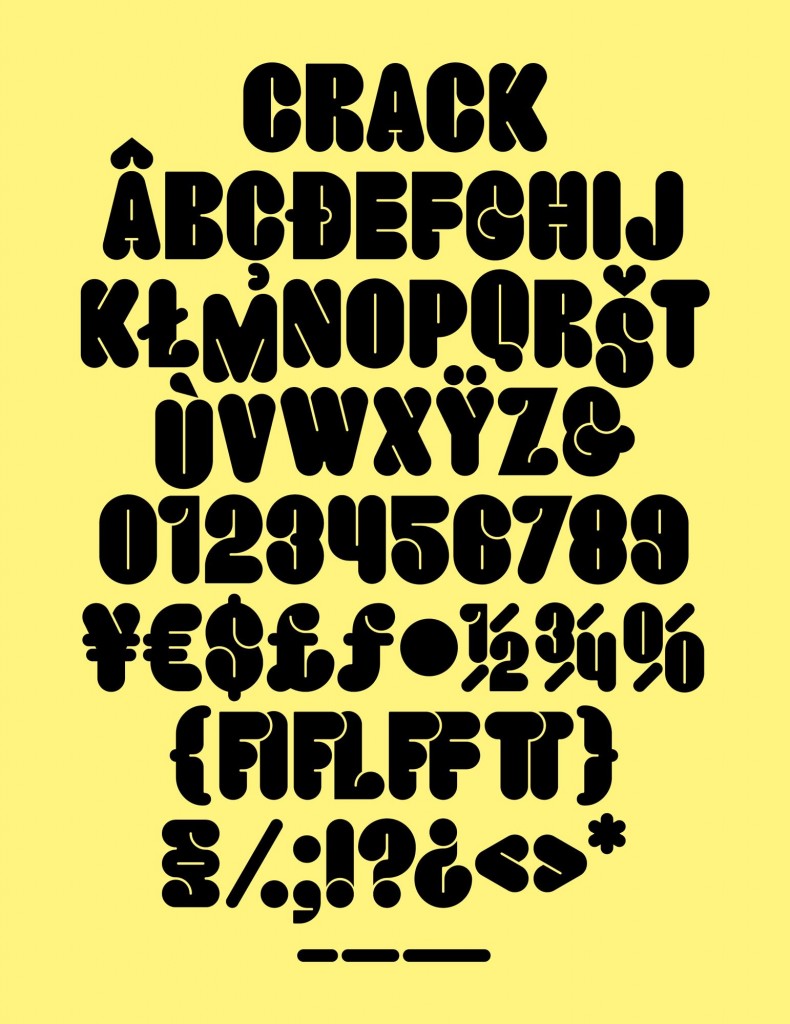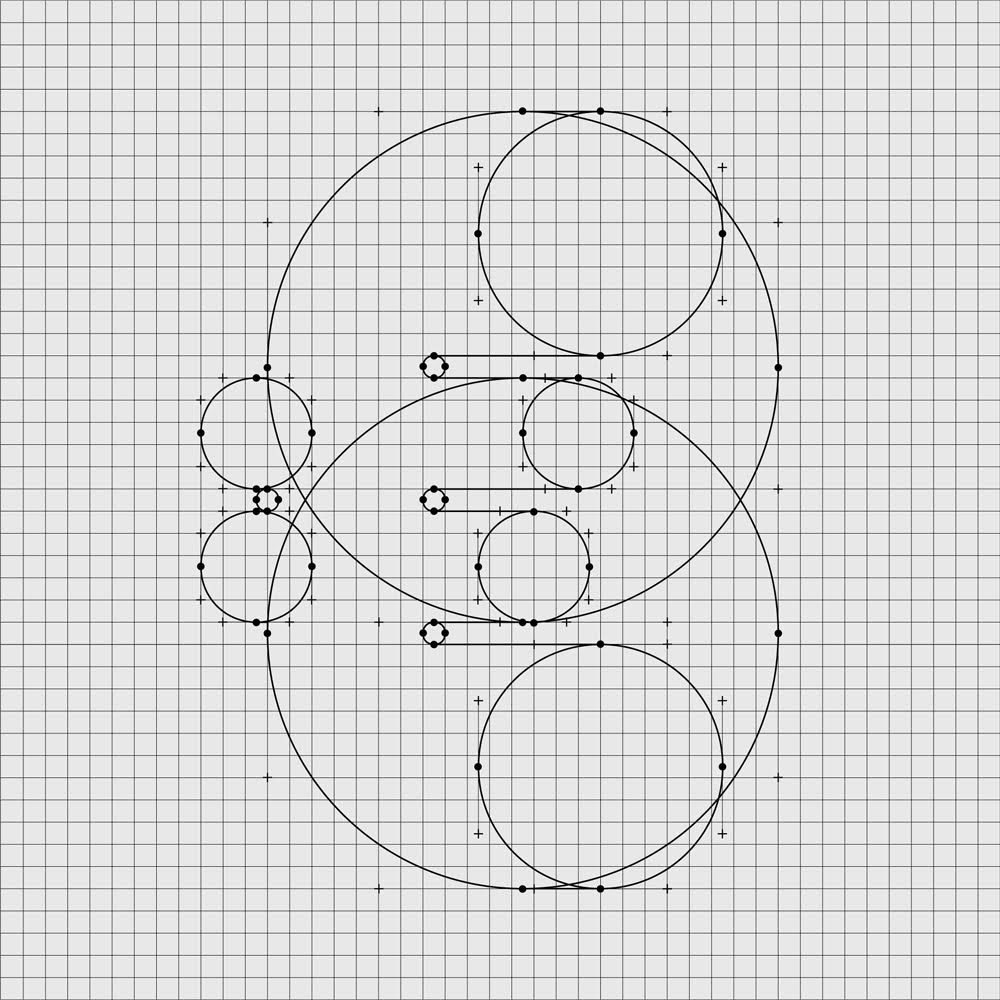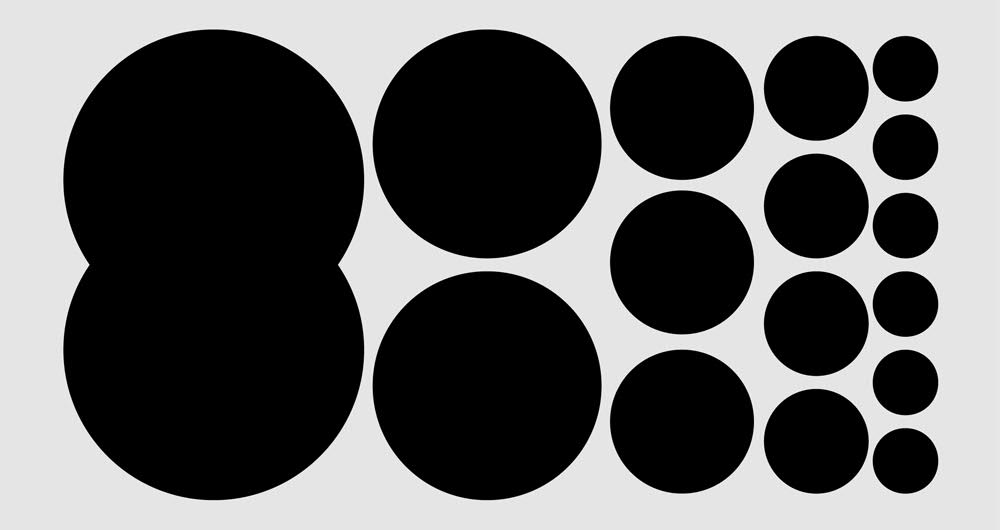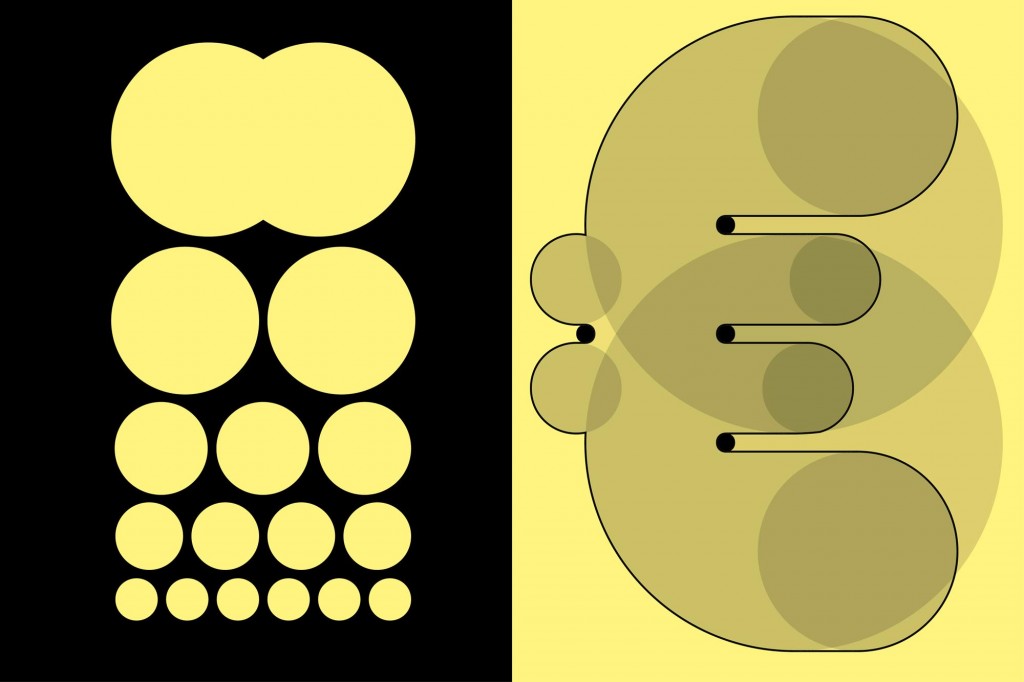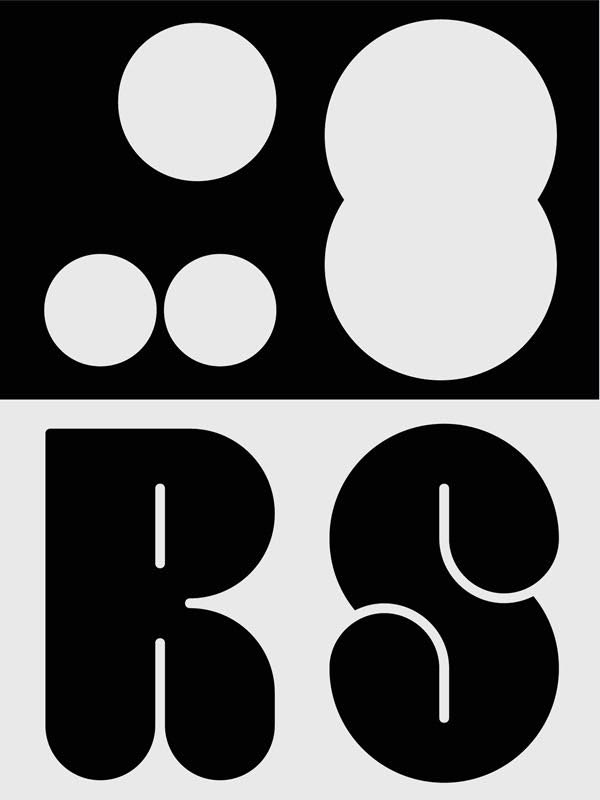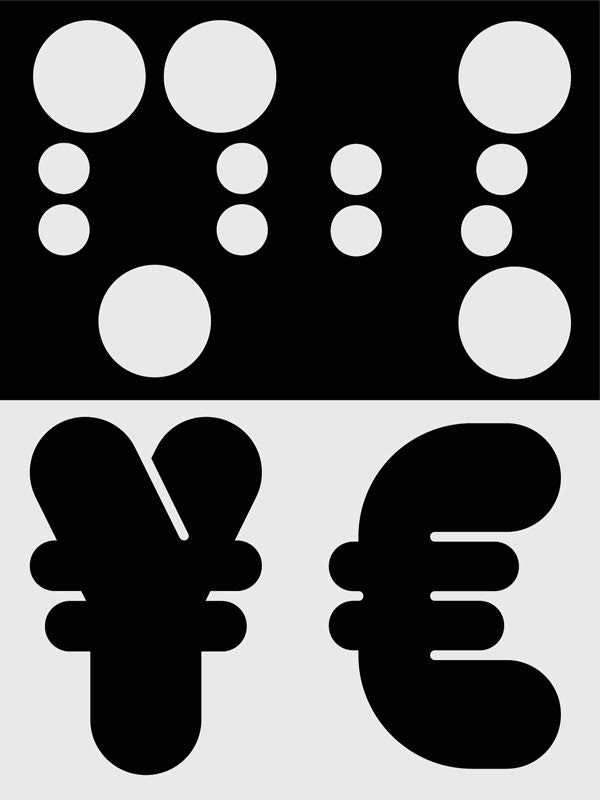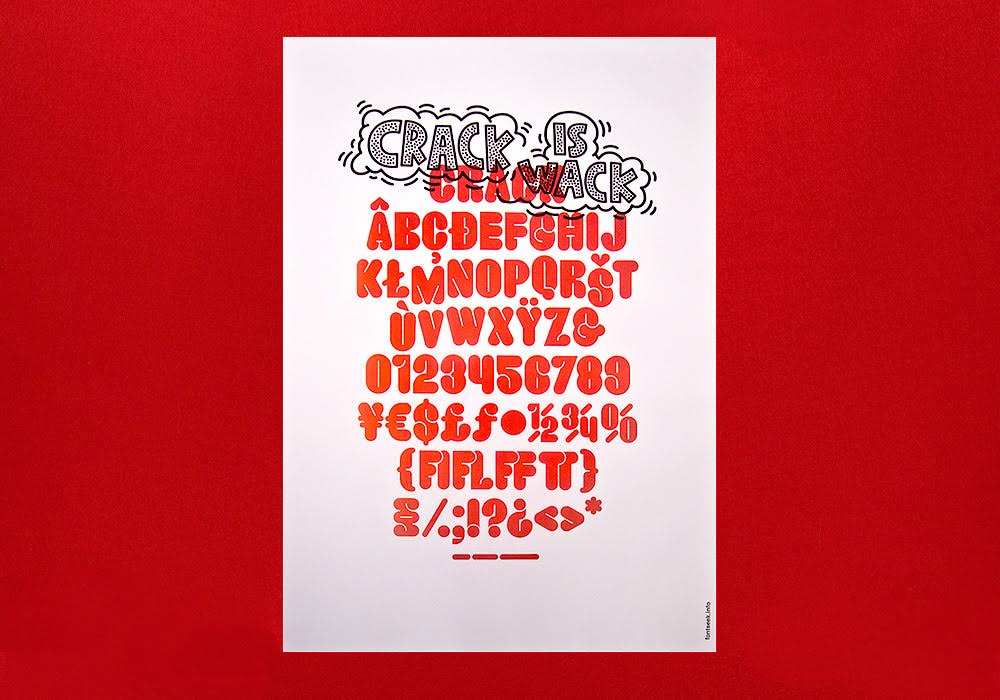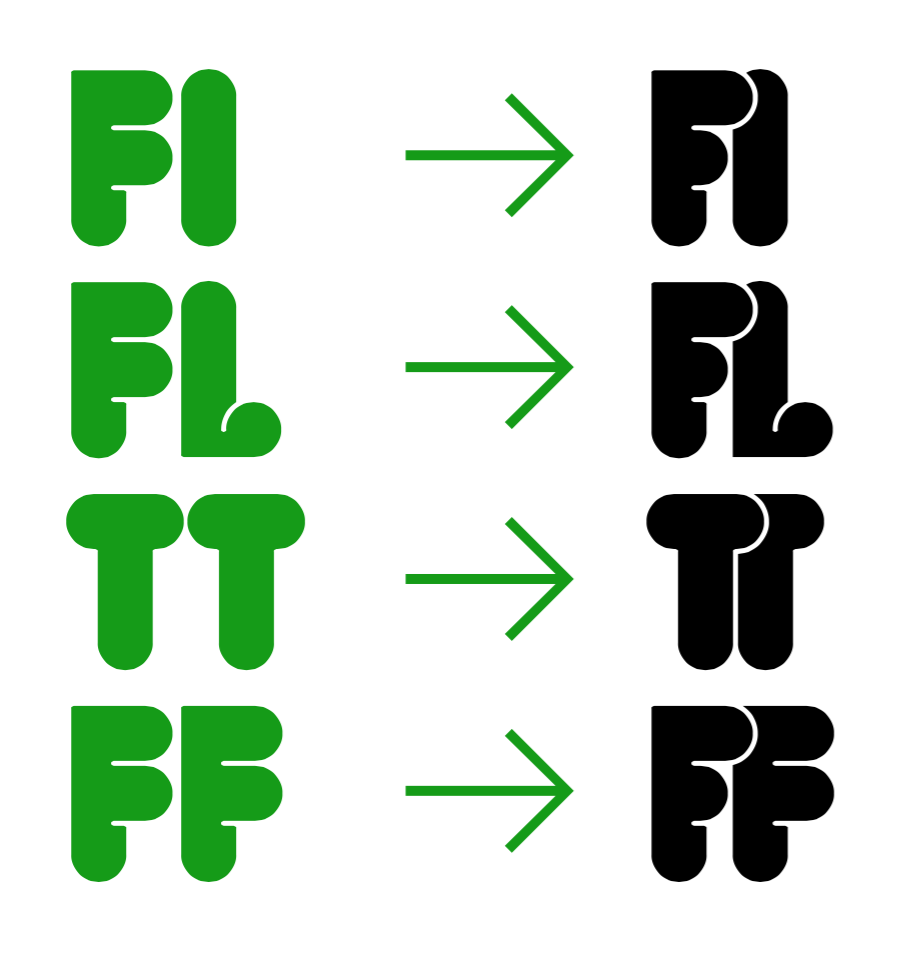
고유한 서체들(Unique Fonts) : Crack
본 연재는 국내외의 개인 혹은 기업에서 제작, 서비스하는 폰트 중 독특한 면을 가진 서체를 모아 소개한다. 서체 ‘Crack’은 스위스에서 활동하고 있는 그래픽 디자이너 필립 헤르만(Philipp Herrmann)에 의해서 만들어졌다. 단순하면서도 그 규칙으로 인해 입체감을 느낄 수 있는 것이 특징이다.
고유한 서체들(Unique Fonts) : 2. Crack
스위스 디자이너 필립 헤르만(Philipp Herrmann)이 만든 서체, ‘Crack’
서체 ‘Crack’은 스위스에서 활동하고 있는 그래픽 디자이너 필립 헤르만(Philipp Herrmann)에 의해서 만들어졌다. 이 폰트는 독일의 디자이너인 어윈 포엘(Erwin Poell)의 폰트 ‘Tuba’를 재해석한 서체이다. ‘Tuba’에 비해 면은 좀 더 일정하게 잘라졌고, 더욱 현대적인 형태를 목표로 만들었다. 작은 크기로 사용될 때에도 선명도를 유지하기 위해 둥근 영역의 비중이 미세하게 확장됐다.
Crack의 모티브가 된 서체, ‘Tuba’
본래 어윈 포엘이 디자인한 ‘Tuba’에서는 하나의 면을 구획했다면, ‘Crack’은 보다 과감한 방식으로 좀 더 겹쳐 보이게끔 자른다. 일종의 착시로 가상의 입체감을 부여한다. 여타 입체적인 서체들은 원근감을 이용해서 3D에 가까운 이미지를 표현하는데, ‘Crack’은 단순하면서도 그 규칙으로 인해 입체감을 느낄 수 있는 것이 특징이다.
또, 글자끼리의 레이어를 통해 추가적인 입체감을 더 만들어 낼 수 있다는 것, 사용자가 임의로 글자를 겹쳐서 만들어 내기 전에 글자끼리 충돌 했을 때 입체감을 미리 만들어 놓았다는 점이 흥미롭다.